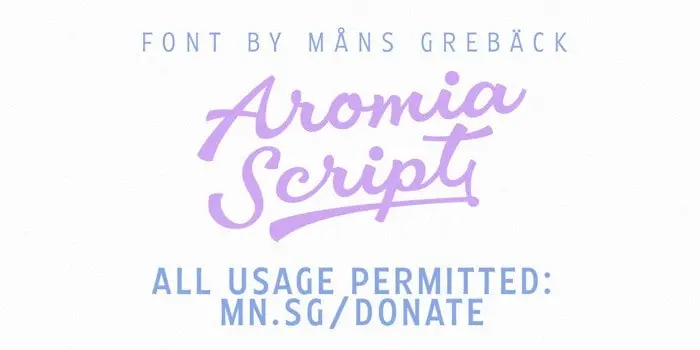
Aromia Script Font
Aromia Script Font é uma fonte tipográfica script vintage criada por Mans Greback com um toque de pincel para dar vida a esta fonte e torná-la mais audível e chamativa aos olhos. Com uma mistura de estilo, ela se destaca perfeitamente como opção para criar marcas de marca, ilustrações ou mesmo designs para roupas. Esta fonte não apenas aprecia línguas multilingues, mas também números e símbolos. O catálogo da Aromia Script Font inclui três versões: Regular, Rough e Edge. Sua versatilidade em um único pacote torna esta fonte uma escolha ideal para designers que desejam adicionar sofisticação e personalização a seus projetos. Ideal tanto para aqueles buscando uma solução de design minimalista quanto para os criativos que procura algo mais expressivo, Aromia Script Font é uma excelente opção para designers gráficos. Seja em sua forma suave ou mais marcante, esta fonte atinge com perfeição a essência do script: fluida e vibrante, enquanto mantém o charme vintage.